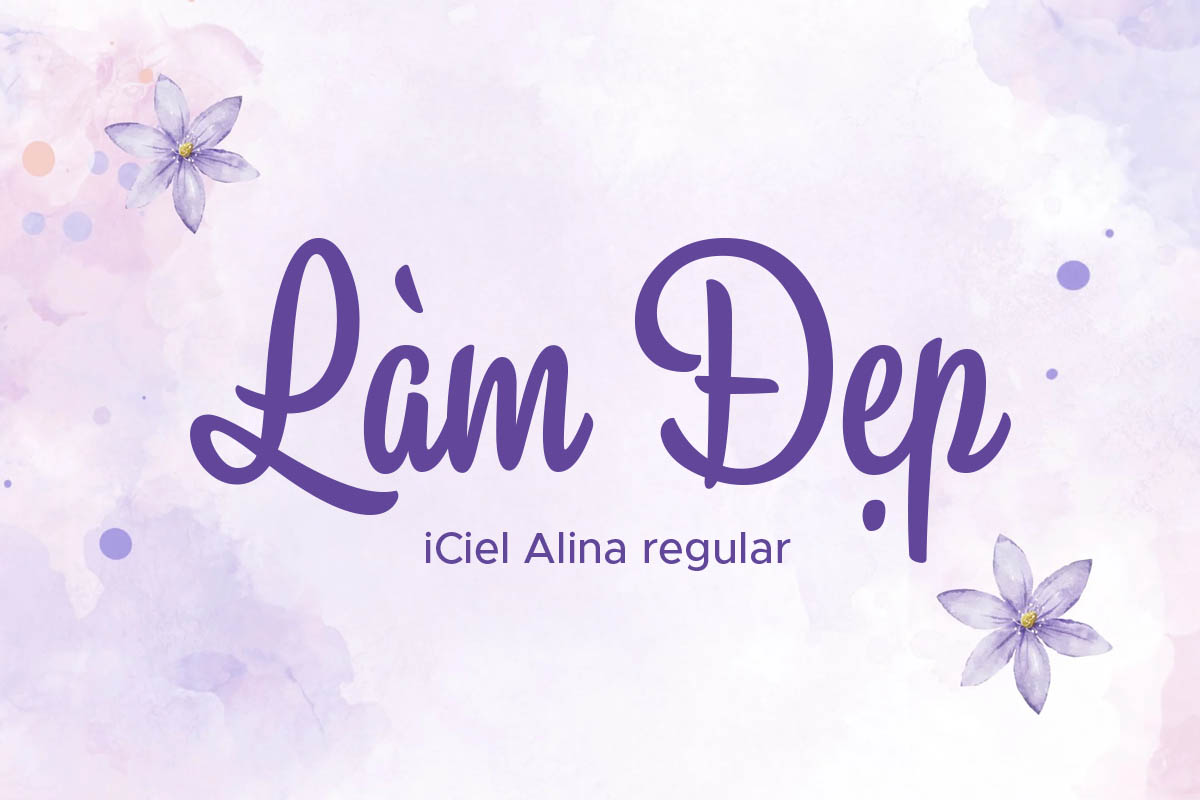
Font chữ iciel alina Việt Hóa - Miễn Phí
Tác giả Måns Grebäck
iCiel Alina regular
Font iCiel Alina là một trong những bộ font chữ viết tay Việt hóa được nhiều designer ưa chuộng bởi sự mềm mại, bay bổng và đầy nữ tính. Kiểu chữ này mang phong cách handwritten hiện đại, đường nét uốn lượn tinh tế, tạo cảm giác gần gũi nhưng vẫn chuyên nghiệp. Trong thiết kế, iCiel Alina đặc biệt phù hợp với các dự án mang tính sáng tạo, lãng mạn hoặc nghệ thuật như thiệp cưới, poster, typography, logo thương hiệu cá nhân, bìa sách và các sản phẩm truyền thông mạng xã hội.
Font Alina ban đầu được thiết kế bởi Måns Grebäck, một nhà thiết kế nổi tiếng với nhiều bộ chữ nghệ thuật độc đáo. Sau đó, font đã được iCiel – một nhóm thiết kế font tại Việt Nam – Việt hóa trọn bộ, bổ sung đầy đủ dấu tiếng Việt và tinh chỉnh kerning, giúp cộng đồng sáng tạo Việt dễ dàng sử dụng mà không gặp lỗi hiển thị.
Điểm mạnh nổi bật của font iCiel Alina là bộ ký tự được Việt hóa đầy đủ, các glyph được thiết kế đồng đều, hài hòa trong từng câu chữ. Ngoài ra, font còn có khả năng kết hợp linh hoạt với nhiều phong cách font khác để tạo nên điểm nhấn ấn tượng. Với sự thanh thoát và uyển chuyển, iCiel Alina là lựa chọn hoàn hảo cho các thương hiệu, dự án cá nhân muốn thể hiện sự tinh tế và sang trọng.